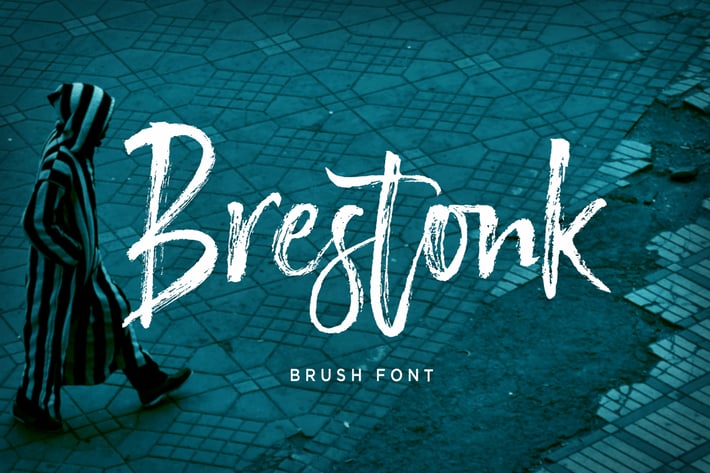
Brestonk Brush Font
Brestonk Brush Font adalah font baru dengan detail stroke bertekstur, juga menyediakan beberapa ligatures dan swash ekstra.
Cocok untuk proyek poster, logo, kemasan produk, undangan, kartu ucapan, merek, berita, blog, semuanya termasuk pesona pribadi dll.